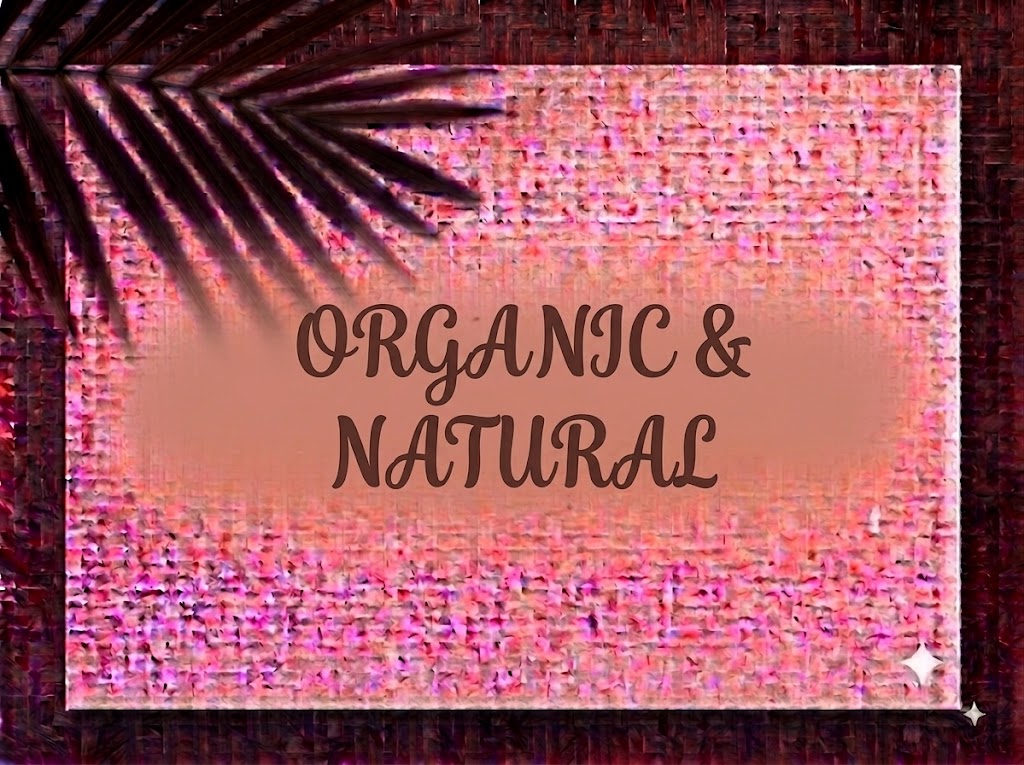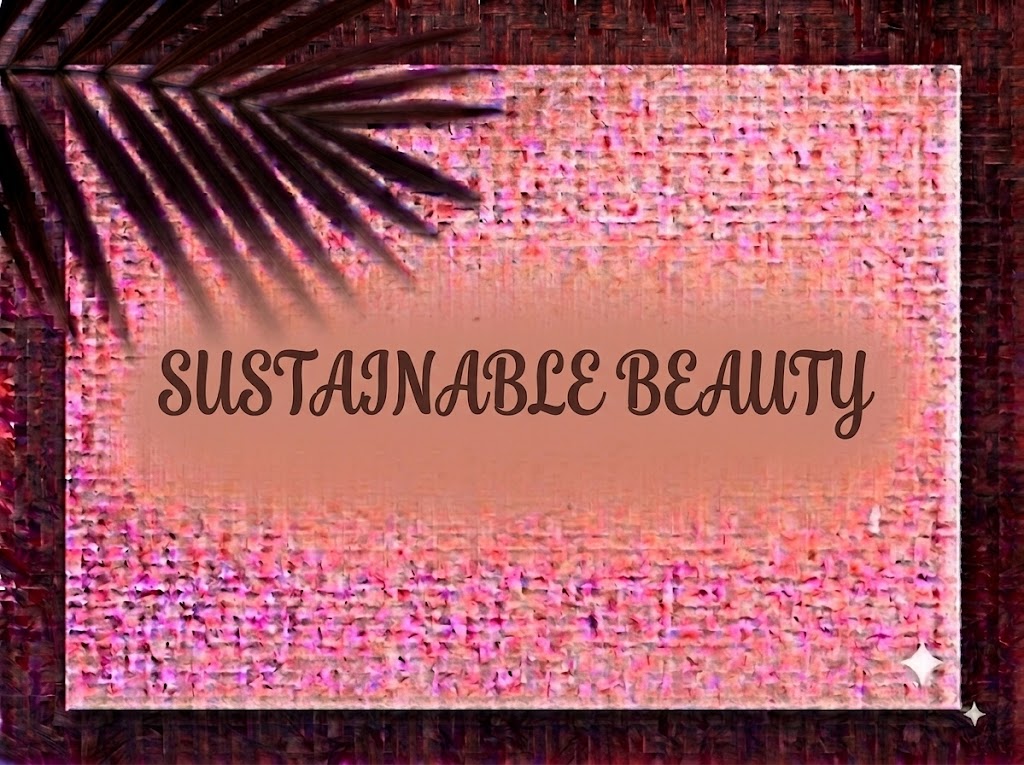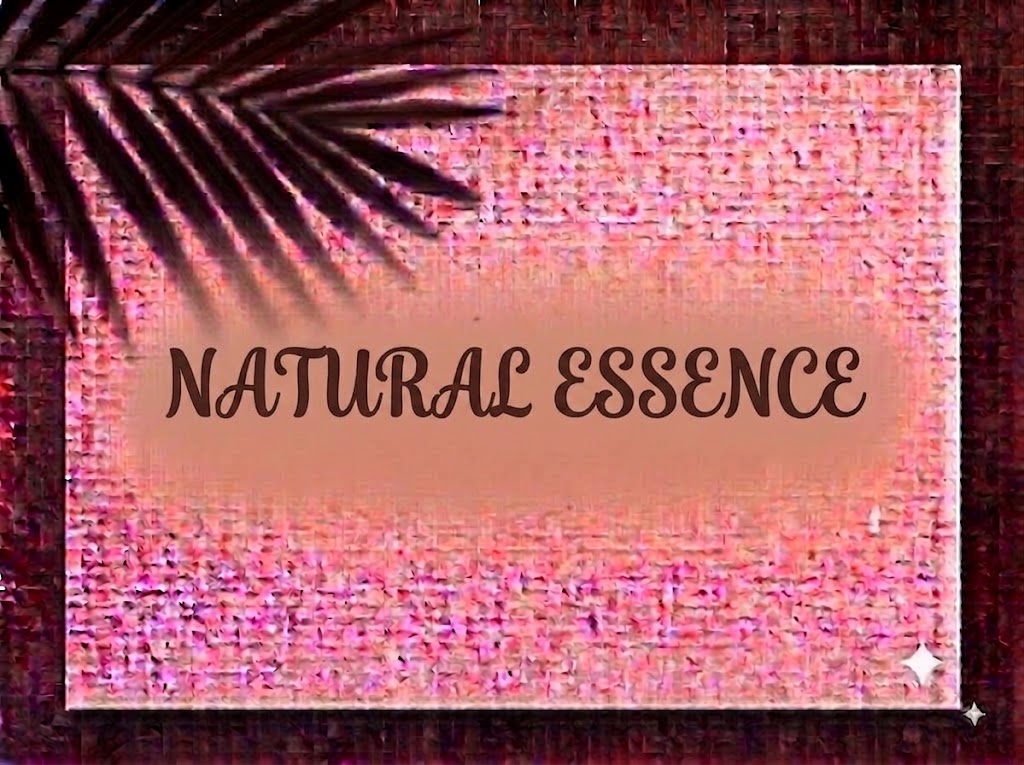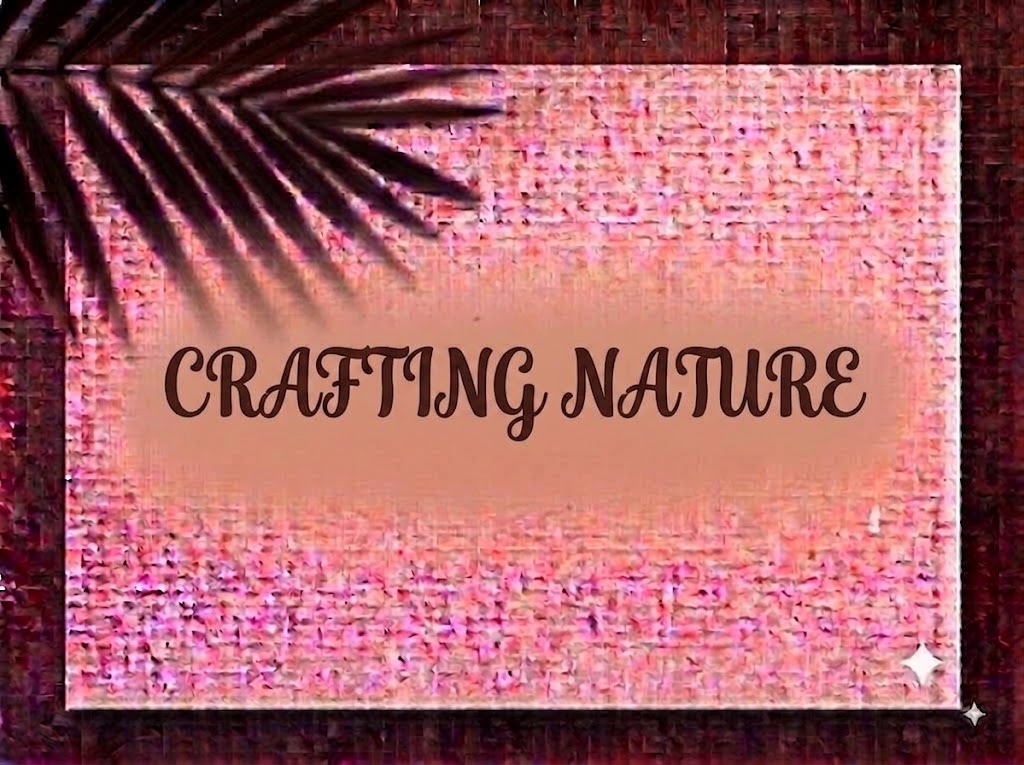
1FTV Kynthia
Trong nghệ thuật thiết kế đồ họa thị giác và sáng tạo nội dung số, những kiểu chữ viết tay uốn lượn (Bouncy Script / Brush Calligraphy) với nét chữ đẫy đà, mềm mại luôn mang lại cảm giác ấm áp, gần gũi và giàu cảm xúc. Khác với các phông chữ viết tay thanh mảnh truyền thống, một bộ chữ script dáng dày (bold cursive) vừa giữ được tính bay bổng tự nhiên, vừa đảm bảo khả năng nhận diện thị giác rõ ràng trên mọi khuôn hình.
Nếu bạn đang tìm kiếm một phông chữ viết tay ngọt ngào, duyên dáng để làm logo tiệm bánh, menu quán café, bao bì thủ công hay tiêu đề video ngắn triệu view, font 1FTV Kynthia chính là mảnh ghép hoàn hảo.
Giới thiệu về font 1FTV Kynthia
Font 1FTV Kynthia là bộ chữ hiển thị trang trí mang phong cách Modern Bouncy Script, nổi bật với các đường nét uốn lượn liền mạch cùng nhịp điệu nhấp nhô vui tươi:
Tên phông chữ: 1FTV Kynthia
Đặc điểm nổi bật của ngôn ngữ thiết kế Kynthia
Sức hút thị giác của font 1FTV Kynthia đến từ sự kết hợp hài hòa giữa nét vẽ bút lông mượt mà và cấu trúc chữ đầy đặn:
Nét chữ đậm đà, tròn trịa (Bold & Chubby Strokes): Trọng lượng nét dầy dặn giúp câu tiêu đề nổi bật rõ ràng trên các phông nền video hoặc hình ảnh chụp thực tế nhiều chi tiết mà không sợ bị chìm nét.
Chi tiết vòng lặp uốn cong (Loop Accents) kiều diễm: Các ký tự có phần đuôi vươn cao hoặc hạ sâu như
b,f,g,h,k,l,y,zđược tạo tác với các nét khuyên uốn tròn mềm mại, tạo nên nhịp điệu đọc nhấp nhô (bouncy) tự nhiên như chữ viết tay thủ công. -
Đồng bộ giữa chữ hoa và chữ thường: Bộ chữ in hoa cách điệu điệu đà kết hợp ăn khớp cùng hệ thống chữ thường nối nét mượt mà, giúp các designer dễ dàng tạo nên những cụm typo headline giàu chất thơ.
Tối ưu hiển thị và dấu tiếng Việt từ 1FTV
Để phông chữ vận hành mượt mà trên cả hai nền tảng Windows và macOS, phiên bản này đã được xử lý kỹ lưỡng về mặt thông số nội tại:
Khoảng cách ký tự (Kerning): Điểm tiếp giáp giữa các nét nối được tinh chỉnh tỉ mỉ, giúp các chữ cái khi ghép thành từ không bị đứt đoạn hay chồng chéo lem nhem.
Bản Việt hóa chuẩn chỉnh: Hệ thống dấu thanh tiếng Việt (sắc, huyền, hỏi, ngã, nặng, mũ, móc) được vẽ đồng bộ với độ đậm của thân chữ, đặt đúng trọng tâm giúp tổng thể dòng chữ tiếng Việt cân bằng và đẹp mắt.
Hệ thống ký tự đầy đủ: Tích hợp trọn vẹn dãy chữ số 0-9 phom dáng mềm mại cùng các ký tự dấu câu, ký hiệu thông dụng.
Đánh giá hiển thị thực tế
Khả năng hiển thị của phông chữ được tối ưu linh hoạt theo nhiều kích cỡ:
Kích thước nhỏ (12pt – 24pt): Nhờ độ dày nét tốt, các câu trích dẫn ngắn và dãy số vẫn giữ được độ rành mạch, dễ đọc trên màn hình điện thoại di động.
Kích thước lớn (36pt – 72pt): Đây là đất diễn lý tưởng nhất để 1FTV Kynthia phô diễn toàn bộ sự duyên dáng, ngọt ngào và các nét bo tròn đầy tính nghệ thuật cho các dòng headline chính.
Ứng dụng trong thiết kế đồ họa và sản xuất video
Sở hữu nét tính cách ngọt ngào, thân thiện và giàu cảm xúc, font 1FTV Kynthia mở ra không gian ứng dụng phong phú:
Video ngắn (TikTok, Reels, Shorts): Dáng chữ uốn lượn hiển thị rất bắt mắt trên khung hình 9:16. Cực kỳ ăn nhập với các vlog nấu ăn, làm bánh, cắm hoa, DIY handmade, video daily vlog hay tâm sự nhẹ nhàng.
Ảnh thu nhỏ YouTube (Thumbnail): Lựa chọn tuyệt vời cho các kênh ẩm thực, lifestyle, review quán café, podcast chữa lành hay video acoustic lofi.
F&B, Tiệm bánh & Quán Café: Hoàn hảo để thiết kế logo chữ, menu đồ uống, nhãn dán ly trà sữa, hộp bánh ngọt (bakery) hay bao bì nến thơm, xà phòng hữu cơ.
Thiệp cưới & Sự kiện: Rất thích hợp làm thiệp mời cưới phong cách Rustic/Vintage, thiệp sinh nhật, bảng Welcome sự kiện hay bìa sổ tay lưu niệm.